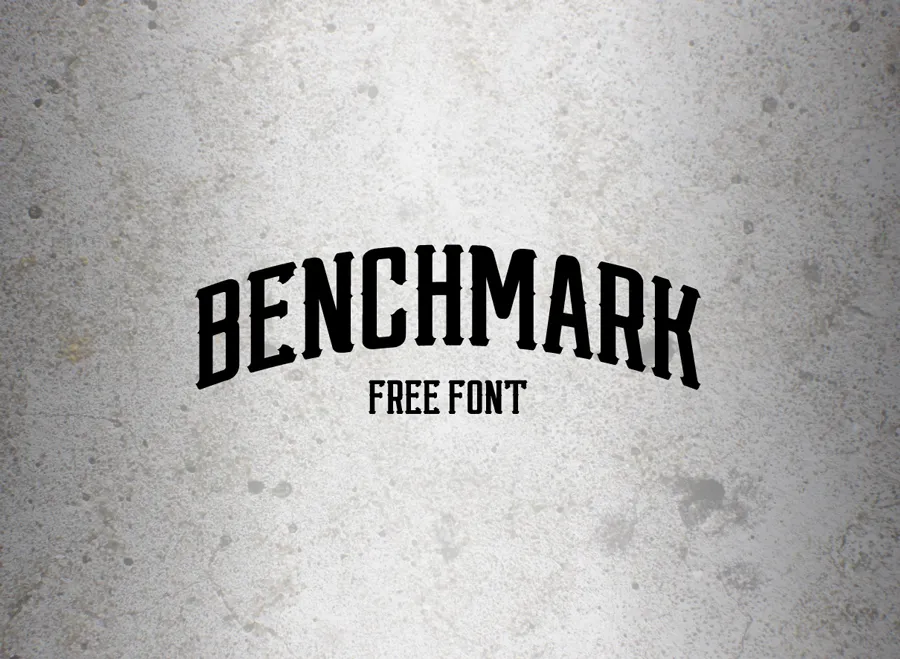
Benchmark é uma excelente fonte para aplicações visuais modernas que valorizam um estilo clássico. Esta família de letras foi projetada por Hamilton e oferece um grau elevado de qualidade, sendo adaptável a múltiplas funções sem comprometer sua estética. Perfeita tanto para desenhos vintage quanto para temáticas retro, Benchmark atua como uma ferramenta eficaz em ambientes que buscam incorporar elementos históricos e esqueletos arquitetônicos no seu design. Suas origens são na identidade visual de times de beisebol, mas sua elegância a torna perfeita para uma ampla gama de projetos visuais contemporâneos. Seja em um poster de arte retro ou em uma assinatura digital moderna, Benchmark será um recurso inestimável.